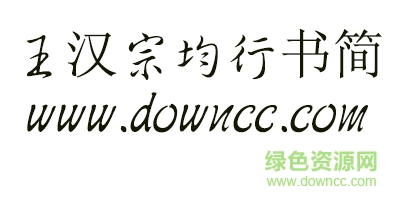
王漢宗均行書簡體是一個行云流水版的行書字體。本字體看起來非常的瀟灑洋溢!可以在設(shè)計浪漫風(fēng)格的作品上使用!女生們都很喜歡的喲!快來下載安裝吧。
王漢宗均行書字體是王漢宗的一款中文行書字體,該字體靈秀清麗、樸茂工穩(wěn)、結(jié)體嚴(yán)整,文字給人以一種獨(dú)特的藝術(shù)感,適用于各類海報、宣傳文件、標(biāo)題等藝術(shù)場合。喜歡的用戶歡迎在綠色資源網(wǎng)下載。